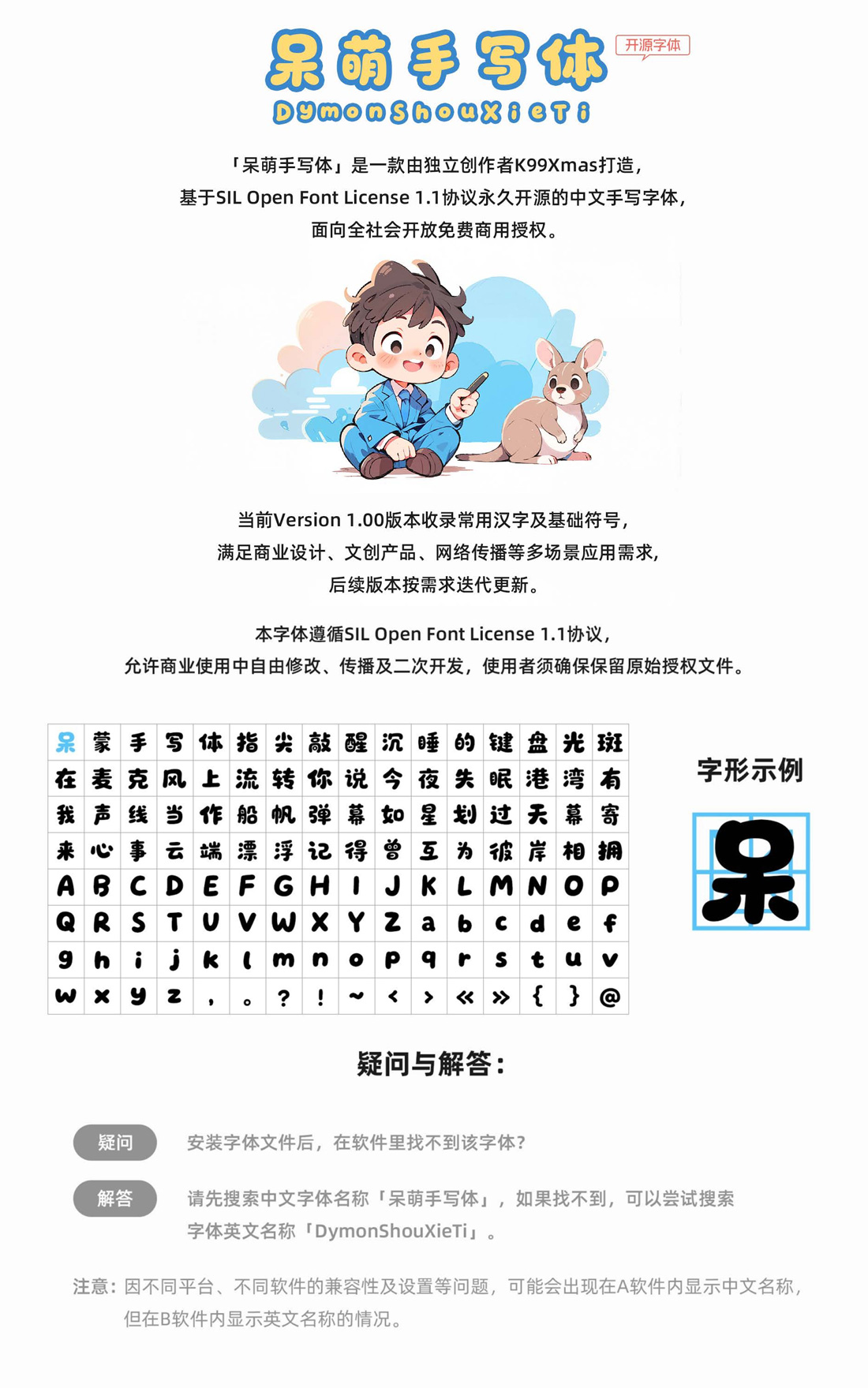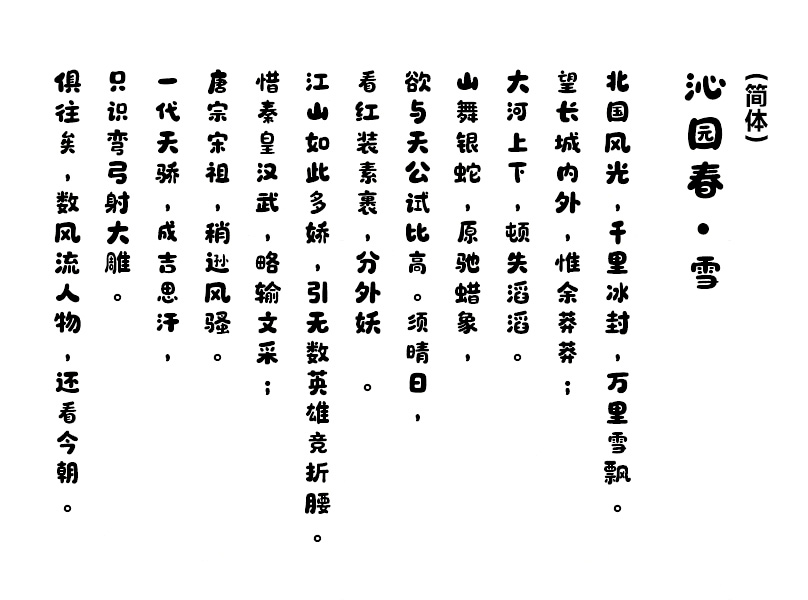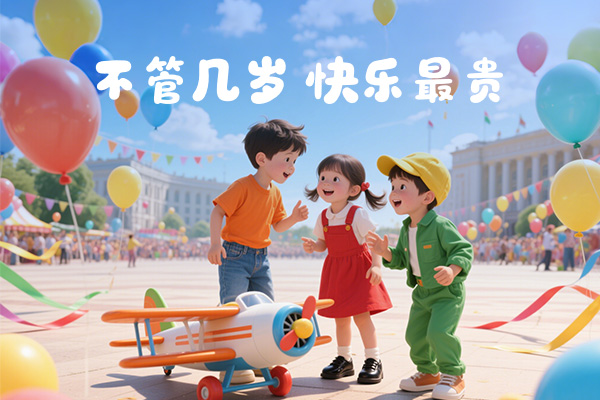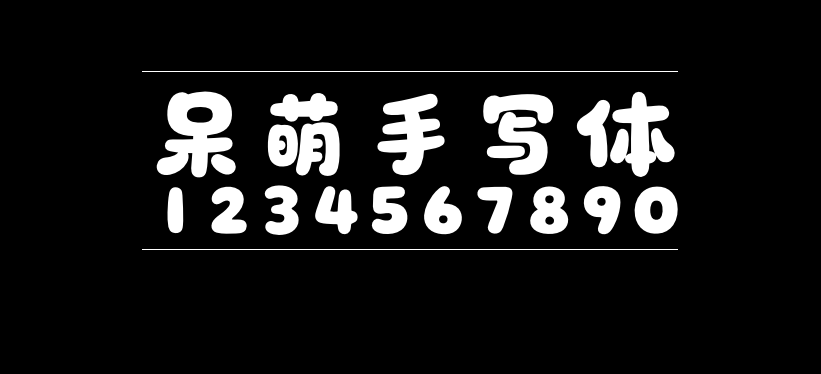
呆萌手写体
呆萌手写体(DymonShouXieTi)是Bilibili独立创作者K99Xmas打造,发布于2025年六一儿童节的一款免费商用字体,这款字体保留自然书写的温度感:圆润造型与稚拙的笔划结构相映成趣,通过灵动的连笔转折与适度的墨迹留痕,营造出充满童真的视觉韵律。每个字符曲线Q弹,既保持文字识别性,又赋予版面独特的治愈系氛围。
当前Version 1.00版本收录常用汉字及基础符号4683个,能基本满足商业设计、文创产品、网络传播等多场景应用需求,后续版本按需迭代更新。
呆萌手写体